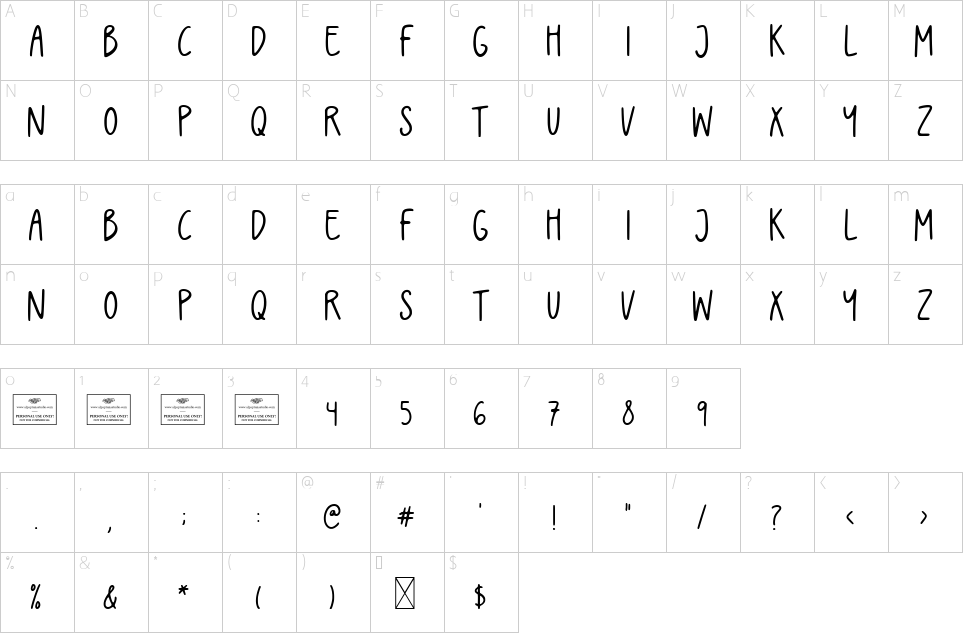
Aqui está uma descrição em português para a página de download da fonte Magic Rainbow, sem inventar características que não estejam na descrição original e seguindo as regras fornecidas: Através de uma inspiradora paleta de cores e formas vibrantes, a Magic Rainbow font oferece um toque de magia em qualquer projeto gráfico. Desenvolvida por Alpaprana, esta fonte leva ao leitor uma experiência visual única que pode transformar simples textos em uma obra de arte. Com 1.630 downloads, a Magic Rainbow não demora a ser percebida como um complemento indispensável para designers e criativos. Seja para gráficos de e-mail, flyers ou até mesmo para criar um logotipo, esta font traz um toque especial à sua composição. Sem dúvida, a Magic Rainbow font se torna um elemento indispensável para aqueles que buscam dar um toque de magia ao design de texto.